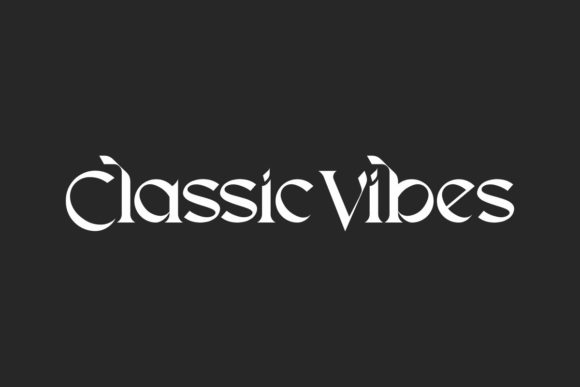
Classic Vibes
適切なデザイン要素を見つけるのは難しい場合がありますが、Classic Vibesは作品を即座に引き立てる優れたコレクションを提供します。
精密に作られたClassic Vibesは、クリーンなベクター、滑らかなタイポグラフィ、そして安心のための商用ライセンスを提供します。
POD(オンデマンド印刷)製品、結婚式の招待状、またはソーシャルメディアのグラフィックを作成している場合でも、Classic Vibesは理想的です。